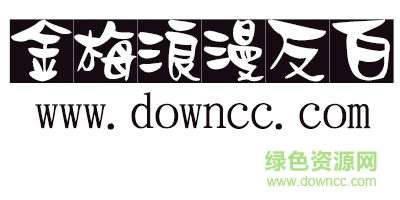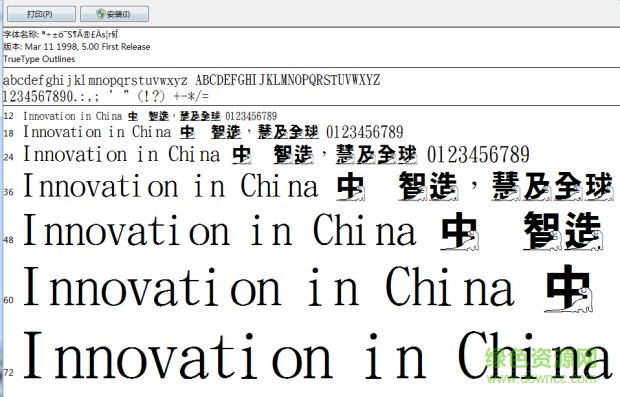
金梅浪漫反白字體輸出的文字效果很個性,這款字體在設計一些大標題的時候還是比較合適的,字體比較醒目,又不失生動!歡迎網(wǎng)友們下載體驗。
金梅浪漫反白字體是金梅字體庫里的一款字體,該字體每一個都是黑底白字,非常適合用于廣告設計、雜志報刊等領域。有喜歡的朋友趕快來綠色資源網(wǎng)下載使用吧!